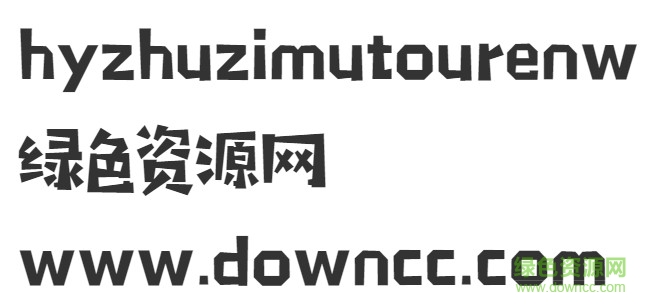
hyzhuzimu tourenw又名漢儀鑄字木頭人w字體,筆劃堅挺有力,線條粗黑,結(jié)構(gòu)隨意,用在海報設(shè)計上效果獨特,視覺效果醒目,喜歡這款字體的小伙伴快來下載吧!
字體造型生動活潑,有鮮明的節(jié)奏韻律感,充滿童趣,十分的有特色,字體整體效果非??蓯郏m用于標志、廣告、游戲動漫、影視等場景。